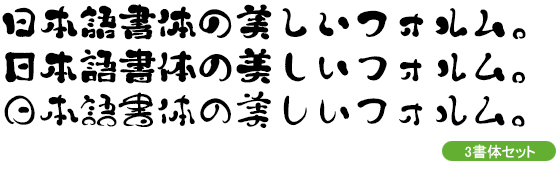
デザイン毛筆
夕力悠光
Takayukoh
「タカ悠」シリーズの1つで、「筆風」としているが「筆」を使ってない手書き書体。柔らかで温かな光り、明るく希望に満ちた光り、溢れる生命の歓喜をイメージ。
タカ書体の紹介
モリサワ社のタカハンドでもおなじみのタイプ作家 高原新一氏が創作する個性豊かなデザインフォントブランド。どの書体も人間味に溢れ、温もりのある魅力的なフォントばかりです。一貫した創作テーマは「手書き風の味わいと温もり」。ファミリーを基本として制作し、多くのデザイナーに親しまれています。